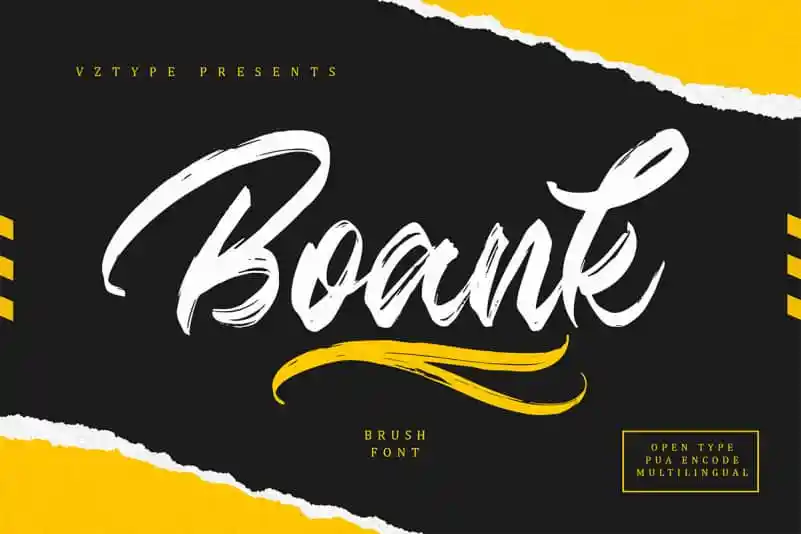
Boank Brush Font – Download Grátis
Boank Brush Font é uma nova adição à coleção de Vztype Script Fonts, desenvolvida para designers de todos os níveis que buscam estilos modernos e minimalistas em suas criações. Seja para projetos de logotipo, materiais de branding, cartões de visita ou mesmo camisas personalizadas, essa fonte é perfeita para qualquer projeto gráfico onde um touch elegante e limpo seja desejado. Ideal para designers buscando expressar uma beleza simples e moderna através de suas criações, Boank Brush Font oferece a oportunidade de incorporar estilos que vão muito além da superficialidade. Este tipo de fonte é perfeitamente adaptável a várias aplicações gráficas, desde o logotipo até os posters, fotos ou até mesmo as tags de imagem em posts nas redes sociais. Seja qual for o seu projeto, Boank Brush Font certamente oferece uma solução moderna e elegante que vai encantar seus clientes potenciais.